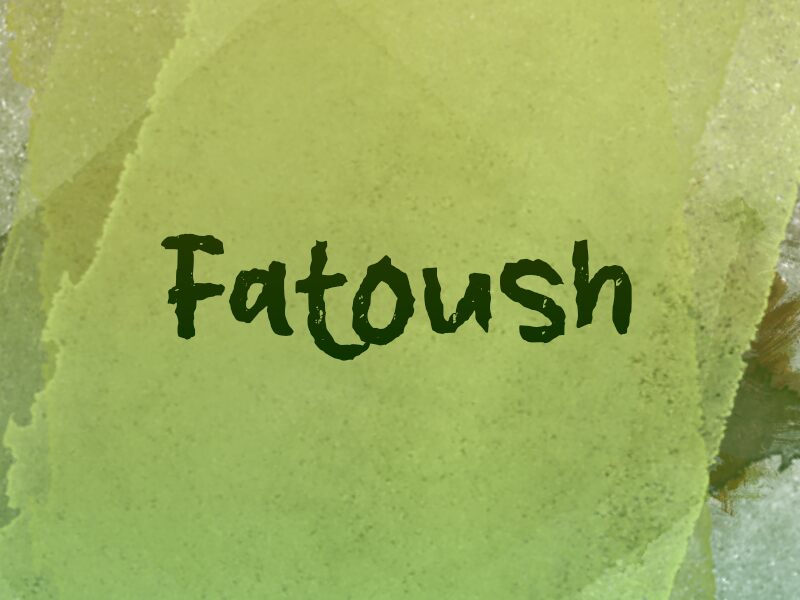
Fatoush od Wep to darmowy, surowy font pędzlowy, który oddaje klimat ręcznie malowanych plakatów ulicznych. Litery wyglądają, jakby ociekały mokrym tuszem – mają grube pociągnięcia, postrzępione krawędzie i swobodne krzywizny, dzięki którym całość sprawia wrażenie bezpośredniej, żywej i celowo „niechlujnej”.
Świetnie sprawdzi się na opakowaniach, okładkach płyt, szyldach kawiarni, plakatach imprezowych i grafikach do mediów społecznościowych, wszędzie tam, gdzie zależy Ci na efekcie odręcznego pisma, a nie komputerowego fontu. Jako darmowy krój, Fatoush idealnie nadaje się też do krótkich nagłówków i tytułów, ponieważ te gęste, wyraziste kształty pędzla niosą ze sobą mnóstwo charakteru, nawet w kilku słowach.
Prezentacja i próbka wizualna czcionki Fatoush